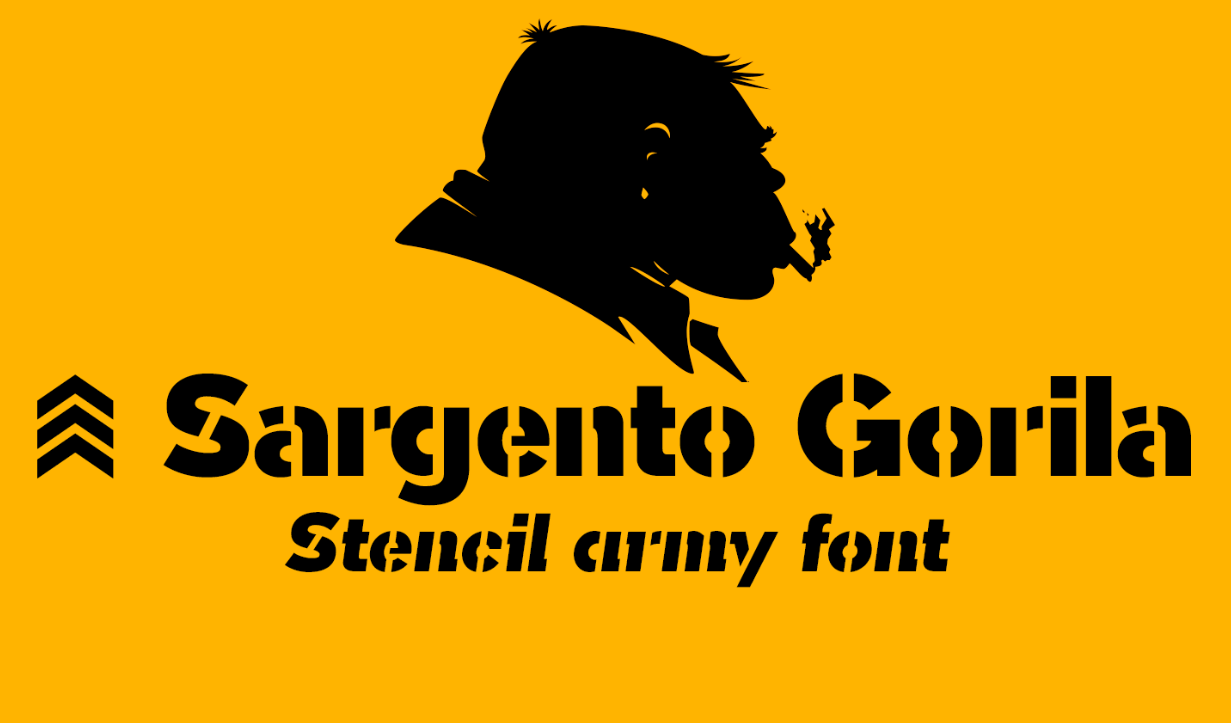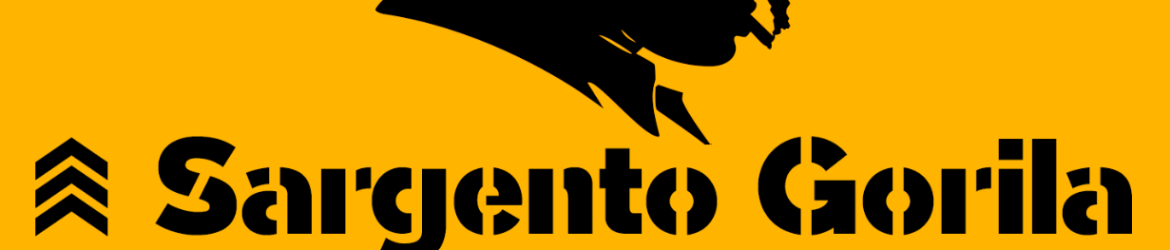
Agora está disponível a Sargento Gorila, uma fonte stencil sem serílato inspirada na estilização militar que oferece um visual único e distinto paraStencil e design de arte. Esta elegante seleção é especialmente interessante para quem busca um estilo forte e distintivo para projetos pessoais e de uso doméstico apenas. Com ligaturas integradas, você pode explorar ainda mais as possibilidades criativas desta fonte inovadora. Defharo, designer do trabalho detalhado, apresenta a Sargento Gorila como uma excelente opção para adicionar um toque militar moderno e elegante aos seus trabalhos de design. Através da Sargento Gorila, você terá a oportunidade de incorporar esse estilo único à sua identidade visual, se tornando uma fonte que é tanto original quanto funcional. Adquira-a agora para explorar as infinitas possibilidades criativas desta fonte sem serílato, perfeita tanto para projetos pessoais quanto profissionais.